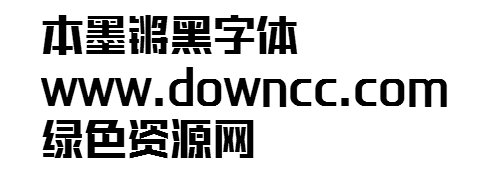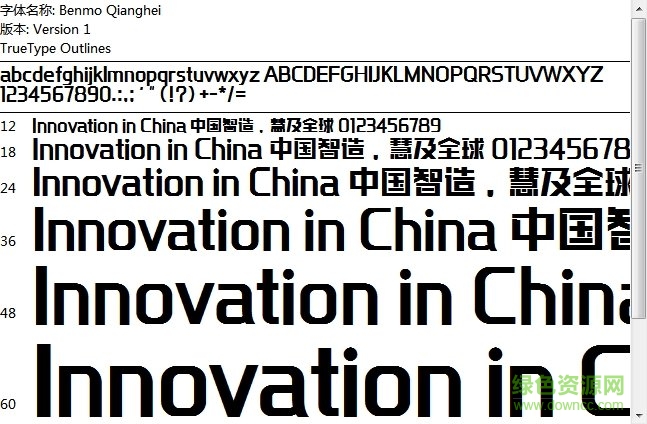
本墨鏘黑字體是本墨字體官方全新上線的一款黑體字體,更為厚重大氣慷慨的造型,極容易給人留下深刻印象,讓你的設(shè)計(jì)更加與眾不同,綠色資源網(wǎng)免費(fèi)推薦!
本字庫(kù)中文以國(guó)家GB2312-80標(biāo)準(zhǔn)設(shè)計(jì)制作,中文字?jǐn)?shù)6763個(gè),另包含ASCII常用字符135個(gè)。
本墨字庫(kù)字體均有著排版印刷字體的特色,顯得更為中正有規(guī)格,而本墨鏘黑比起本墨詠黑、本墨陳黑等更加深刻明朗,可以使用在平面設(shè)計(jì)、包裝設(shè)計(jì)、藝術(shù)設(shè)計(jì)等場(chǎng)合!